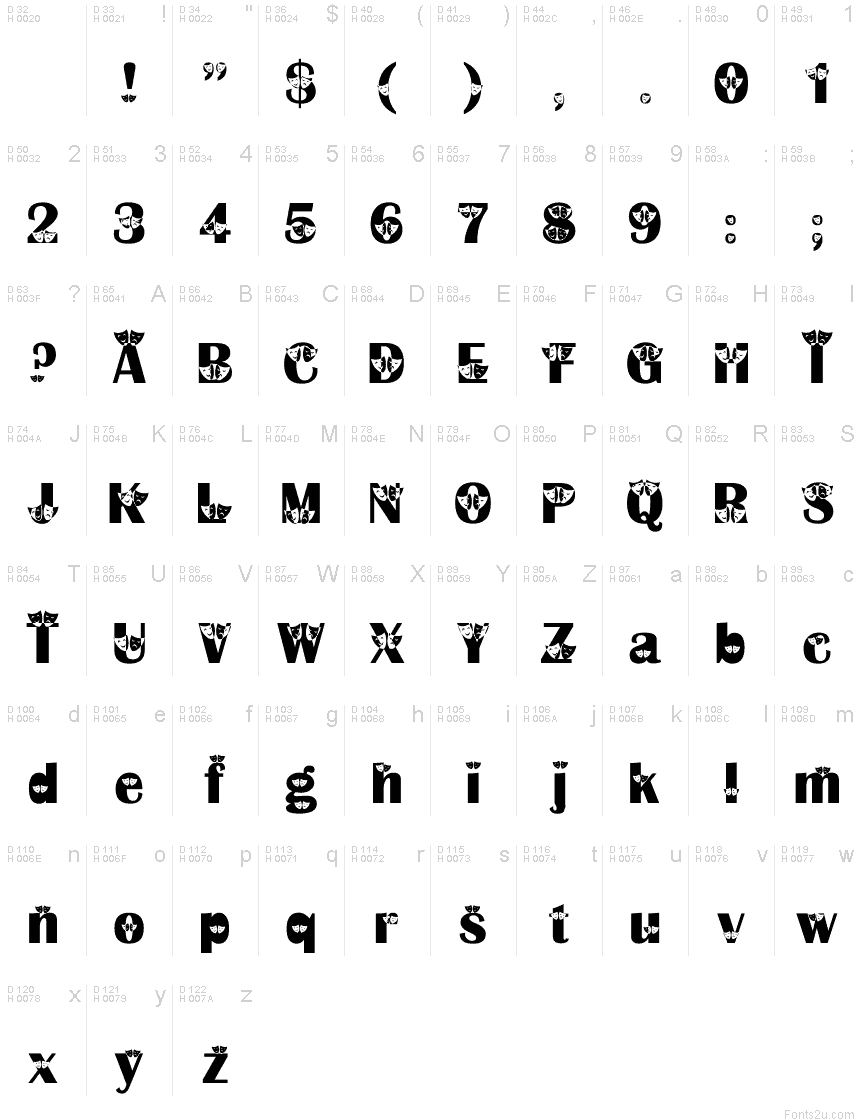
Thespian, di Pearlygates, è un font display gratuito ispirato alle maschere teatrali. È costruito su lettere audaci e arrotondate, che incorporano le maschere della commedia e della tragedia, posizionate in cima o integrate direttamente nelle forme dei caratteri. Questo motivo scenico conferisce al font un tocco di giocosa drammaticità, mentre le sagome spesse lo rendono perfetto per poster dal forte impatto visivo.
Si adatta naturalmente a locandine teatrali, programmi, grafica per festival, loghi di compagnie teatrali e titoli di eventi in cui la tipografia deve esprimere il tema dello spettacolo autonomamente. Essendo un font gratuito, è ideale anche per copertine, cartelli di apertura e brevi titoli che necessitano di un inconfondibile tocco teatrale, senza bisogno di ulteriori illustrazioni.